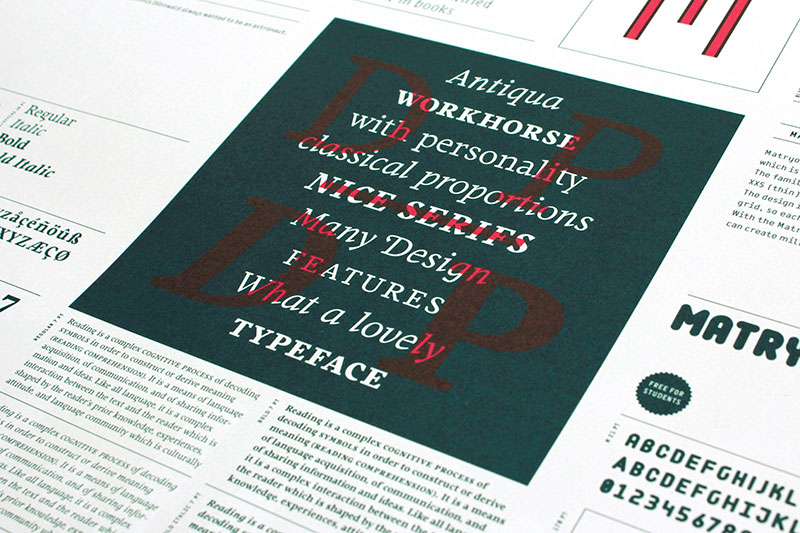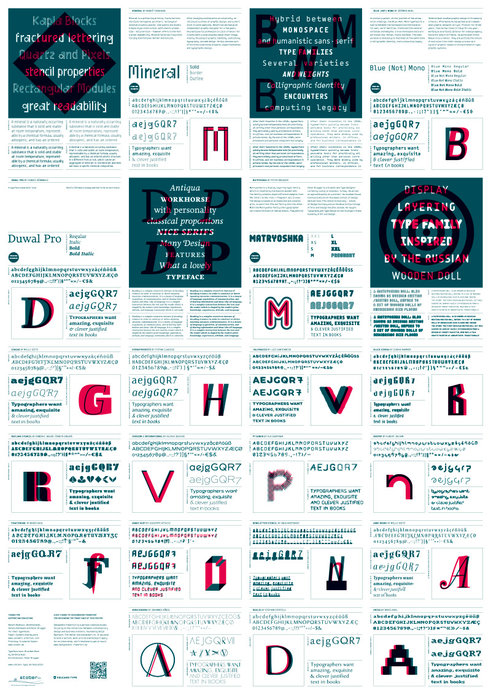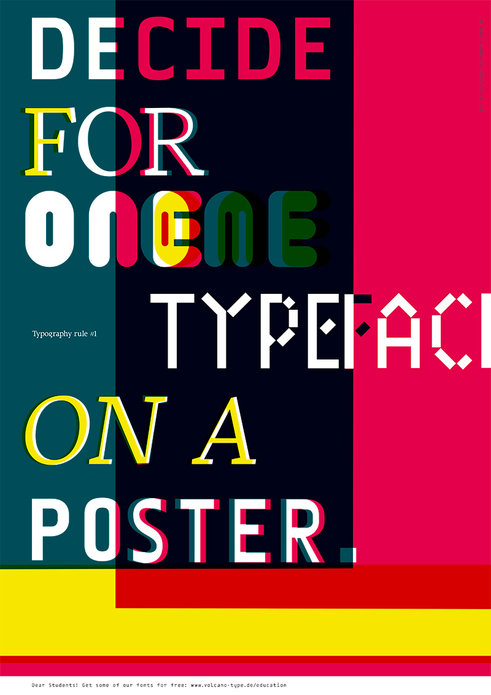
VolcanoType – Education Font Poster #2
Für die zweite Aktion wurde ein schickes DIN A1 Plakat vom Designbüro Frankfurt (Frankfurt, DE) und Peter Brugger (Istanbul, TR) gestaltet (exklusiv erhältlich im Slanted Shop) und vollständig in Sonderfarben gedruckt, welches die aktuell zur Verfügung gestellten Schriften im Kurzprofil vorstellt.
Volcano Type – Education Font Poster #2
Herausgeber: VolcanoType
Schriften: Duwal Pro, Mineral, Matryoshka, Blue (Not) Mono
Gestaltung Vorderseite: Designbüro Frankfurt
Gestaltung Rückseite: Peter Brugger
Duwal Pro by Dennis Dünnwald
The careful balance between the emotional swings and shapes set in strong contrast such as the burly serifs, or generally vertical and orderly appearance within the Duwal Pro determine the special look of this Antiqua typeface. All characters of the Duwal Pro are designed to be open and accessible. The lowercase letters are designed with a large x-height, which is why they are ideal for small font sizes. Many striking details give Duwal Pro a defined and firmer appearance with increasing font size so it is also suitable for use in headlines and work marks. The deliberately constructed and emphasized design of the serifs give the font a strong position and at the same time force the reading direction. Using Duwal Pro in Bold weight, the serifs look clearly striking, the design language is concise and the typeface receives an additional sympathetic force. The Italic weight draws on the expressive but not intrusive design of the Regular, but appears sharper and is ideal for text passages. The font family contains italics, small caps, lots of ligatures, swashes, another format set, contextual alternatives and special characters as well as other open-type features which allow the use of Duwal Pro in 48 languages.
Mineral by Benoît Bodhuin
Mineral is a glittering writing, fractured into multiple tetragonal splinters, rectangular modules slightly spaced, like quartz and pixels. A Kapla style construction, with stencil properties – Solid version – however offers to the font a great readability. Mineral Solid has 2 stylistic titling alternatives: Border and Outline.
Matryoshka by Peter Brugger
Matryoshka is a display layering type family which is inspired by the Russian wooden doll. The family contains eight different weights from XXS (thin) to XXL (fat) + Pregnant (all in one). It was designed by Peter Brugger in 2009/10. The design is based on an elaborate and complex grid, so each font fits perfectly into the other. With the Matryoshka family the typographer can create millions of new solutions.
Blue (Not) Mono by Jéremie Nuel
As a binary system, at the junction to two antagonist drawings, the Blue (Not) Mono typeface is an hybrid between the monospace and the humanistic sans-serif families. Declined to several variants and weights: a true monospace and a proportional one, a roman and italic style, bold and the main purpose is obviously to maintain in the same time a calligraphic identity, and a computing legacy.